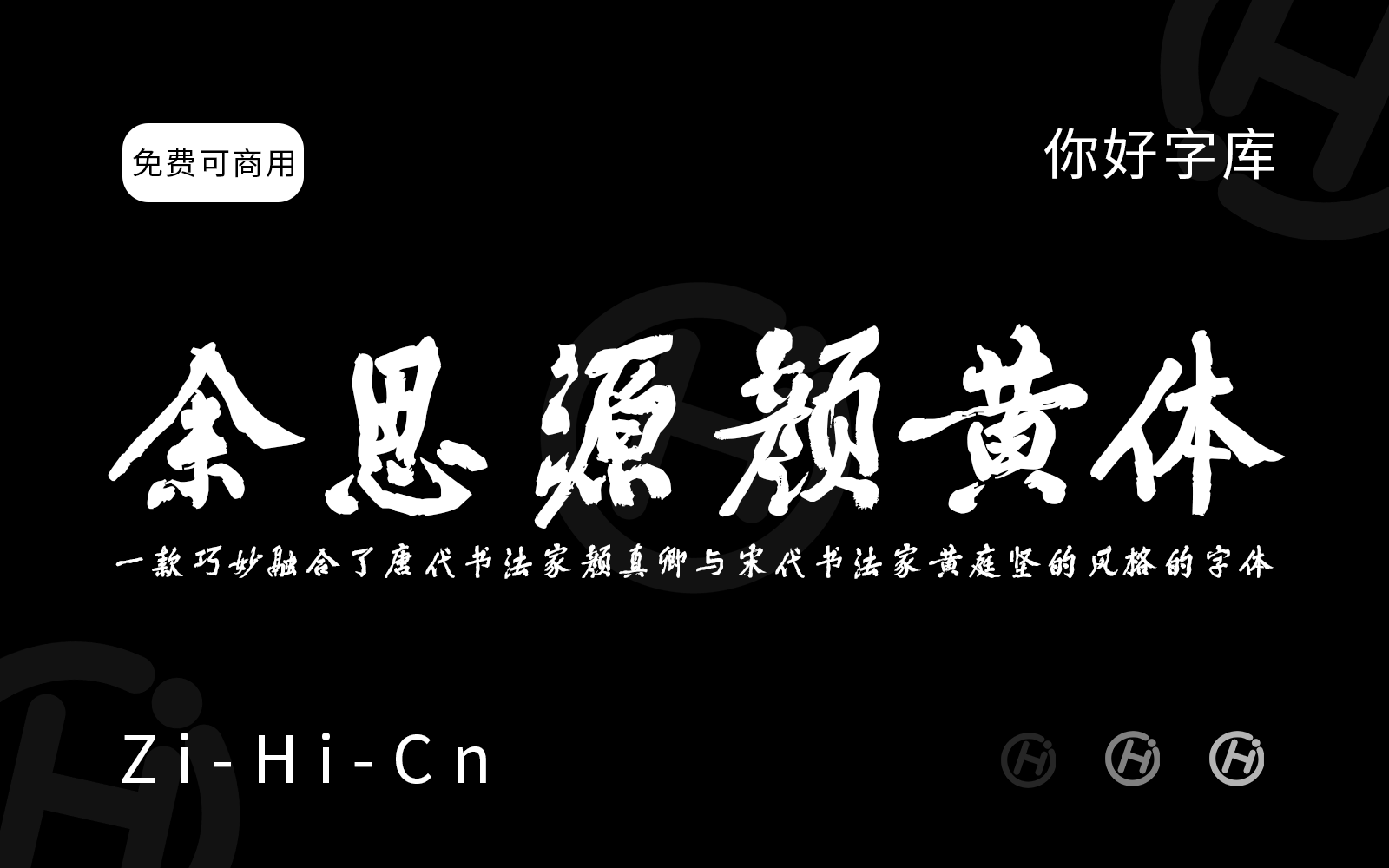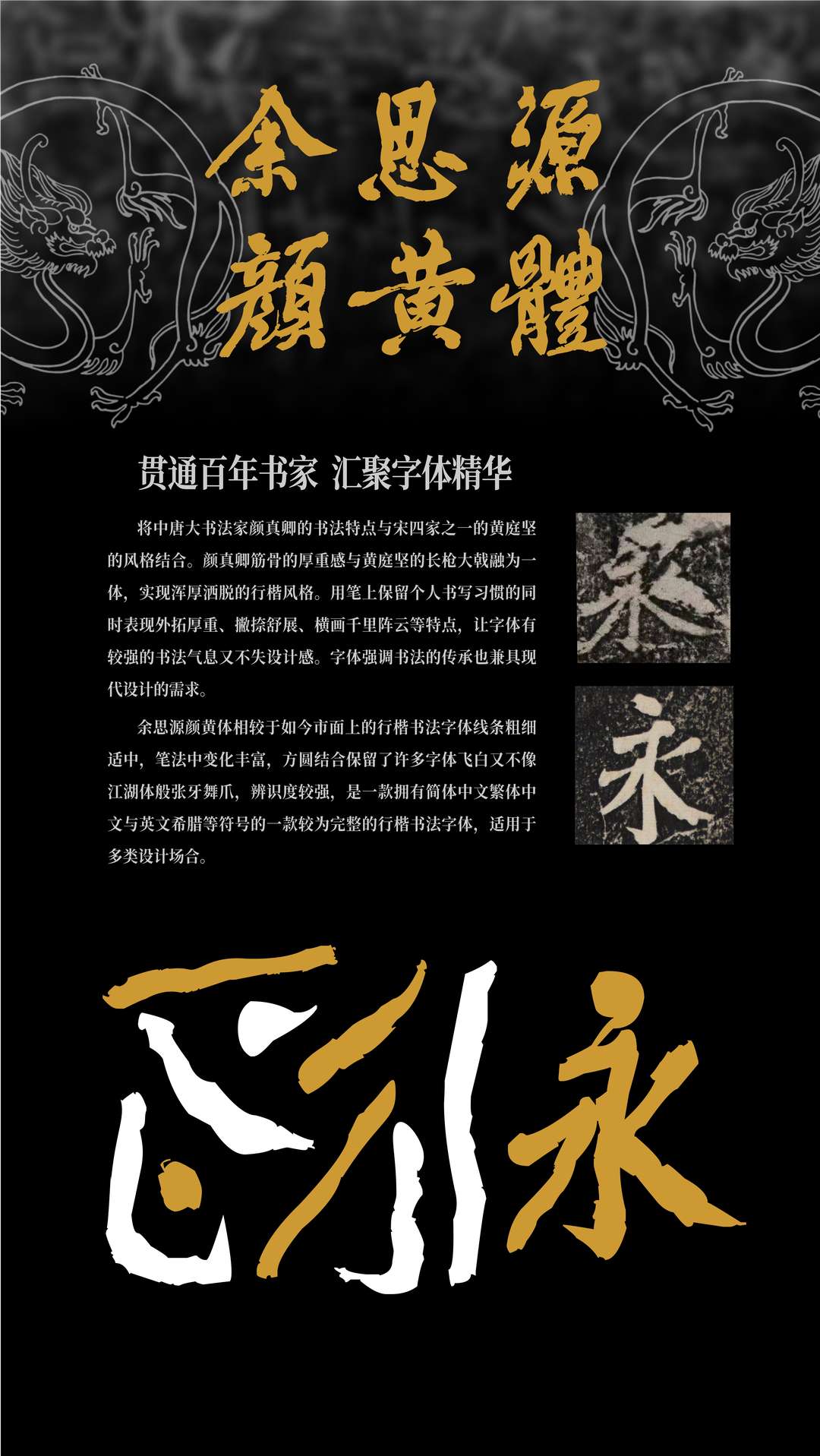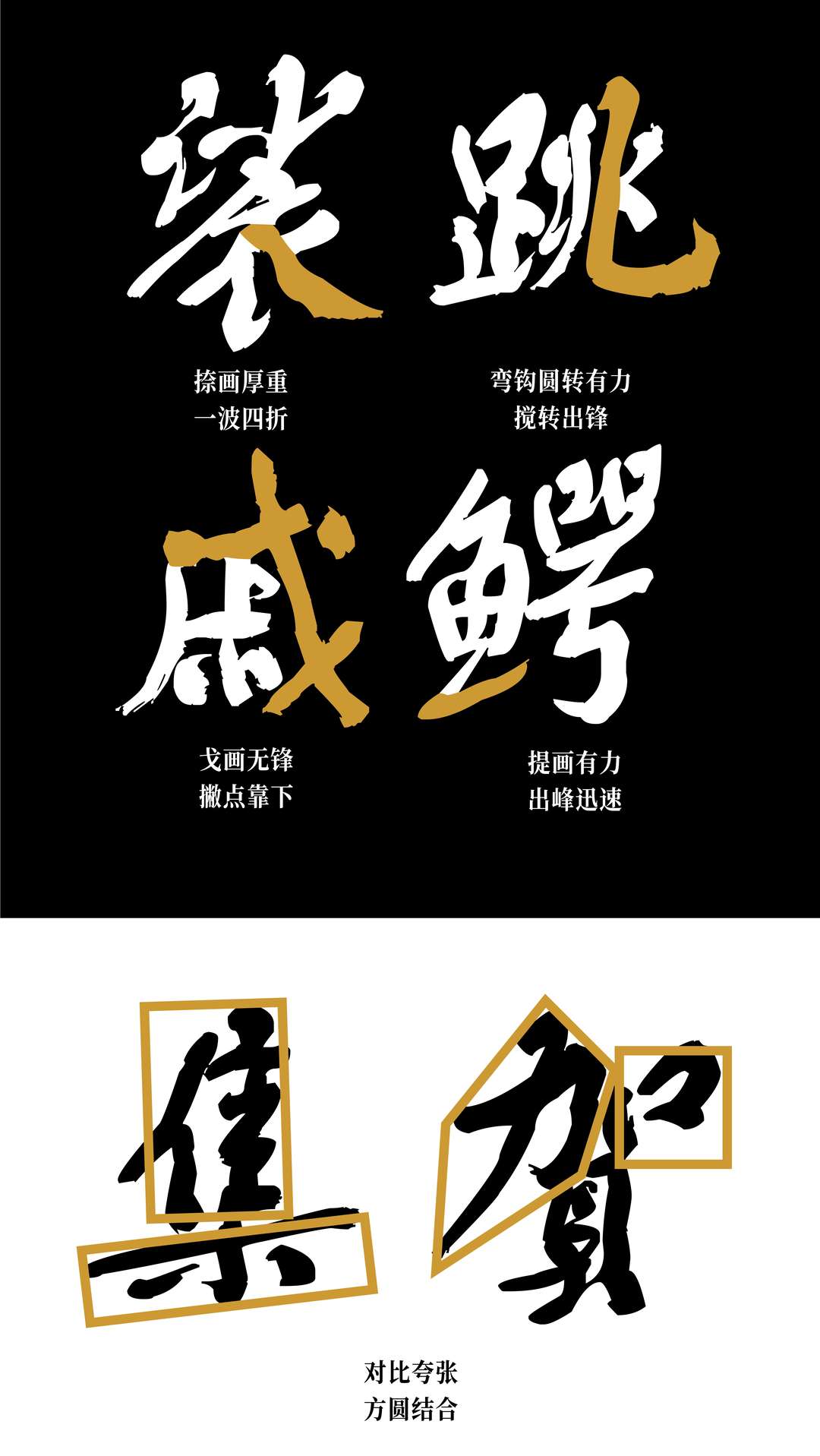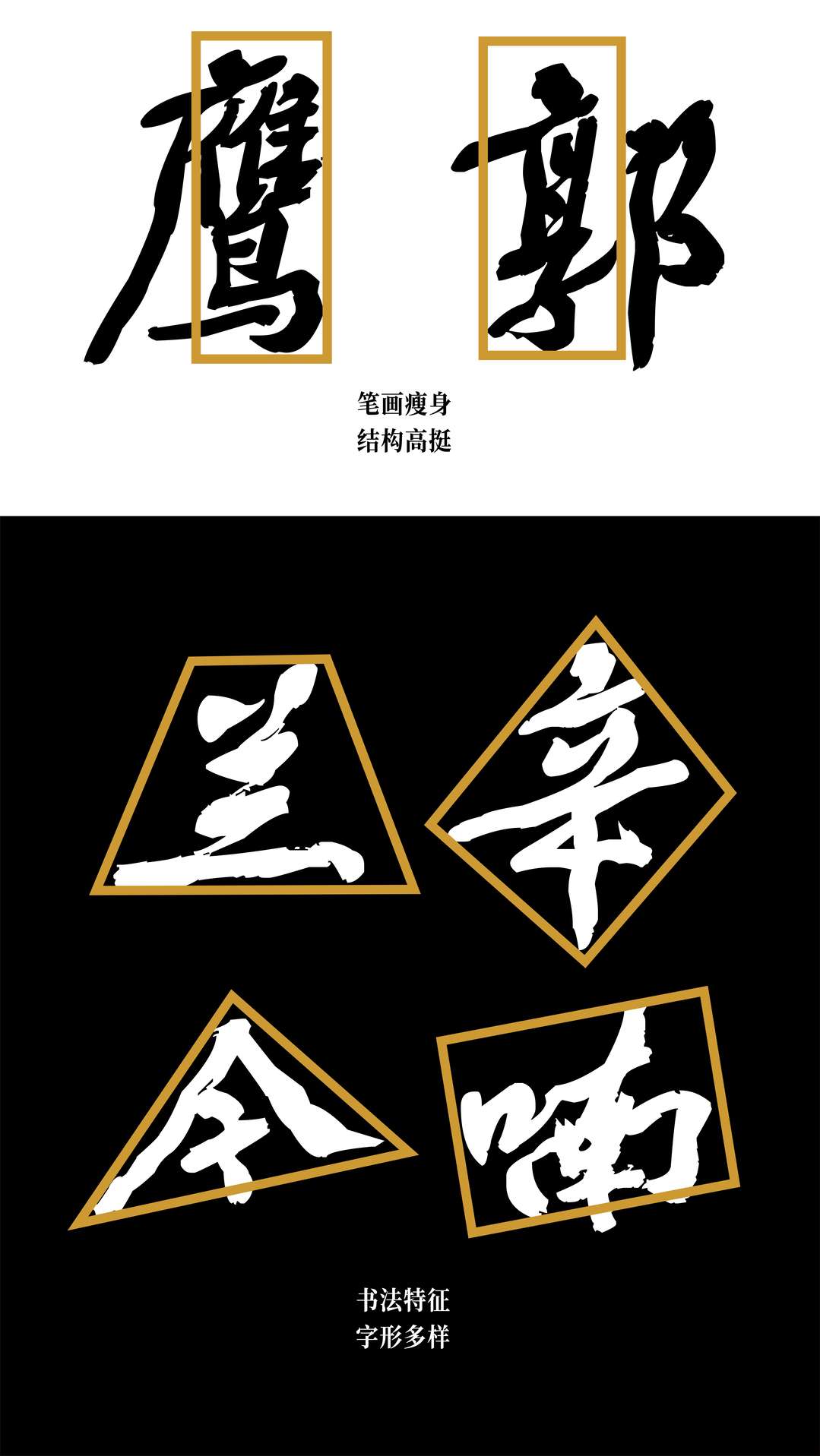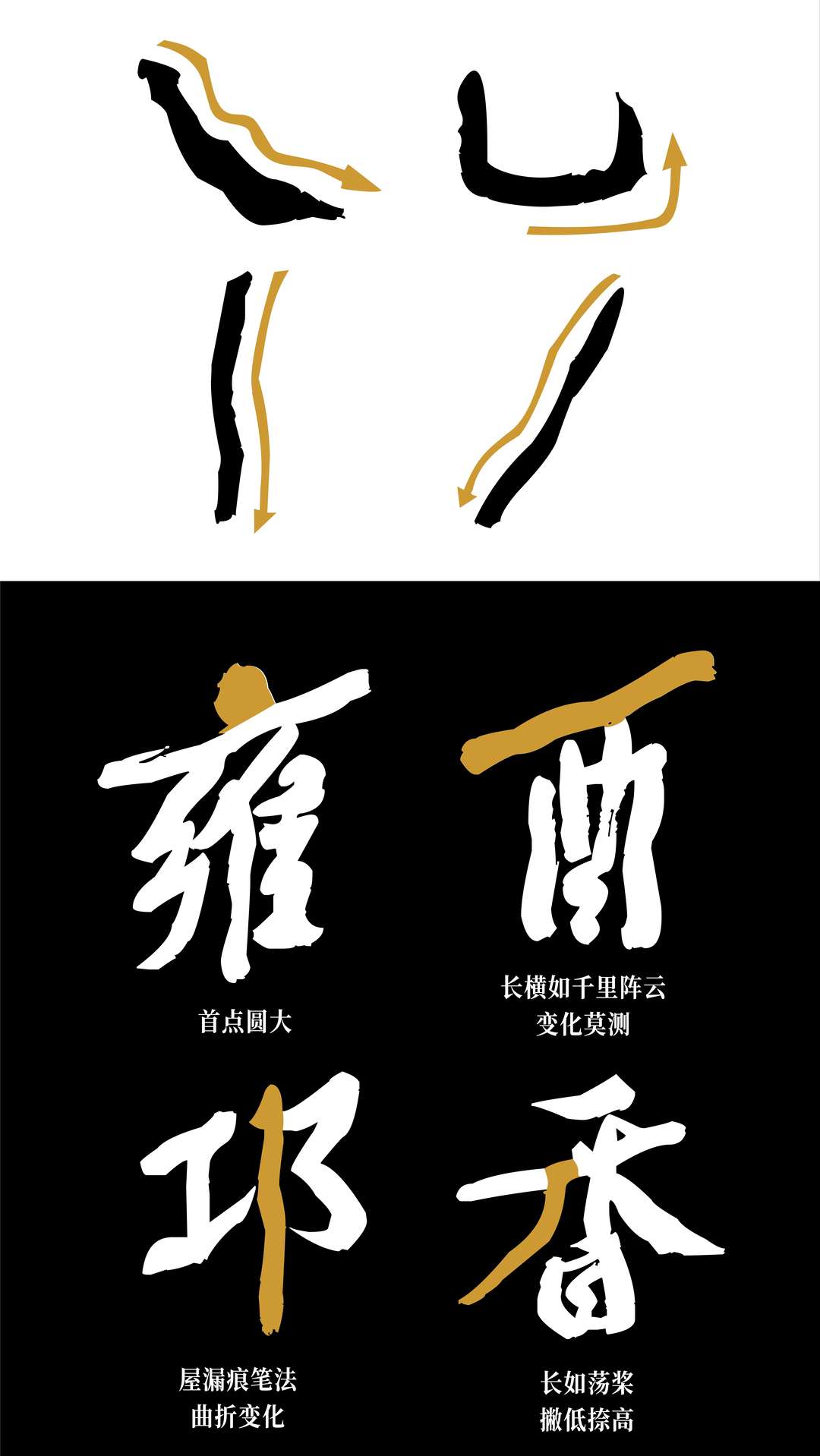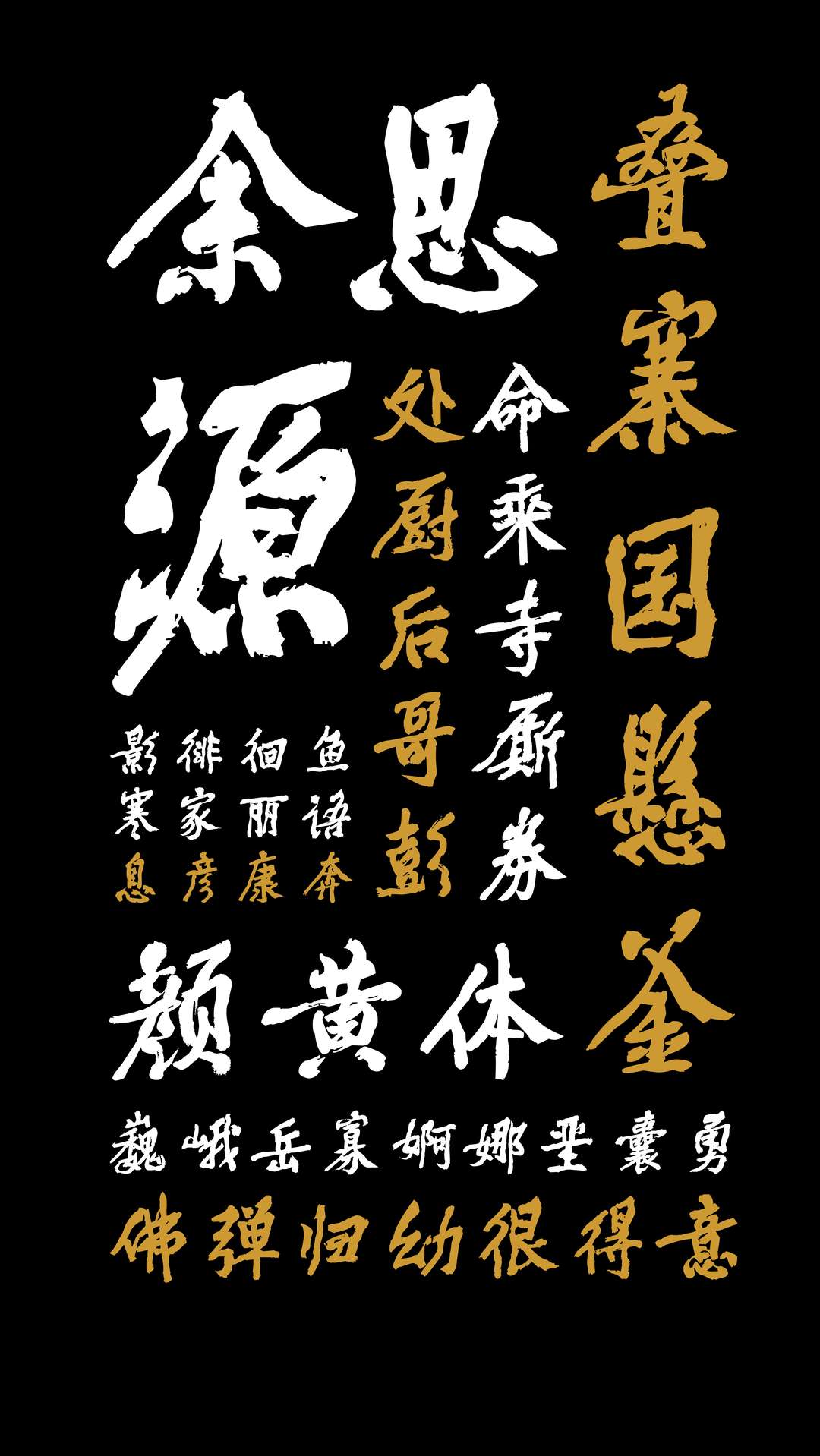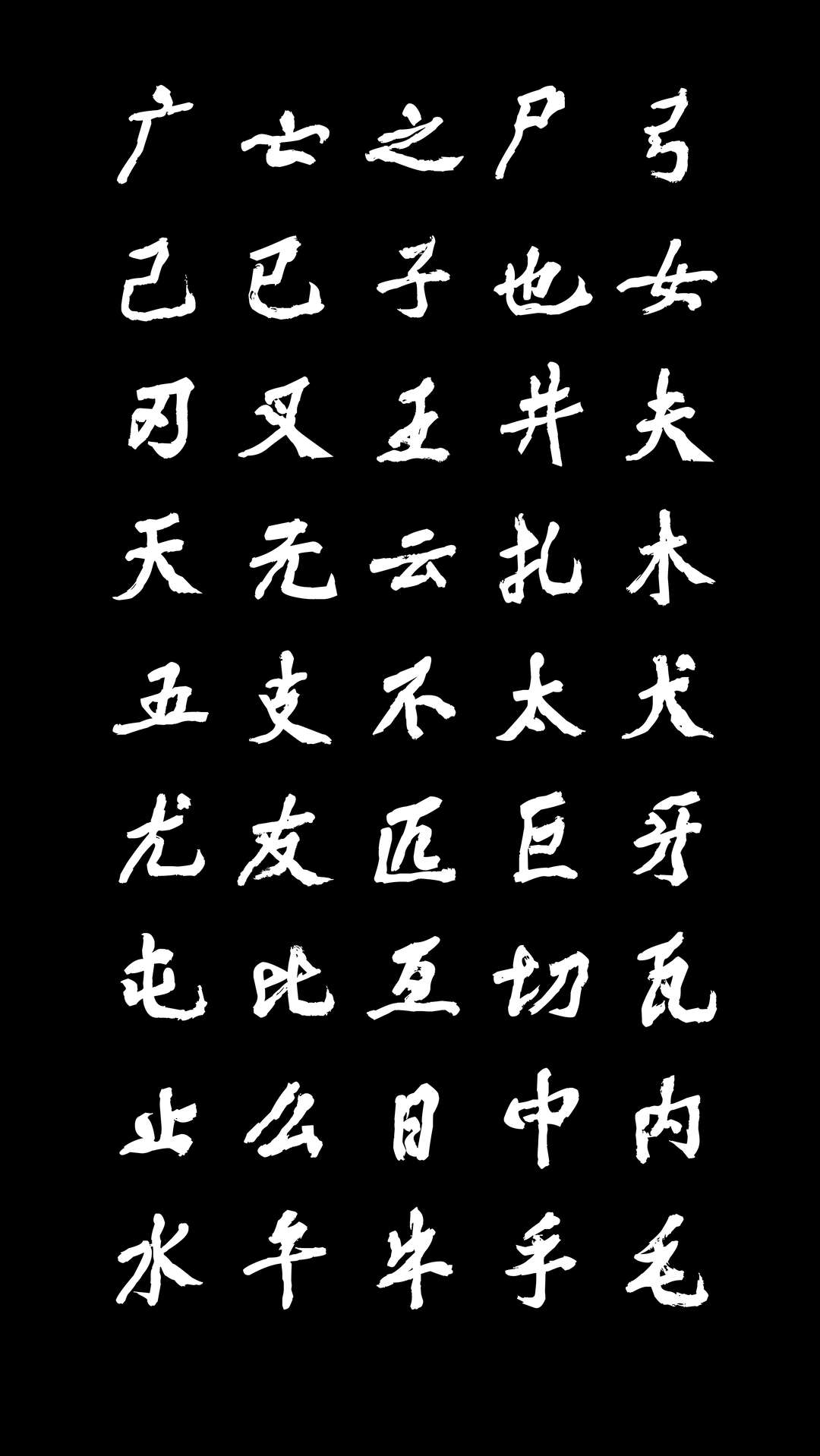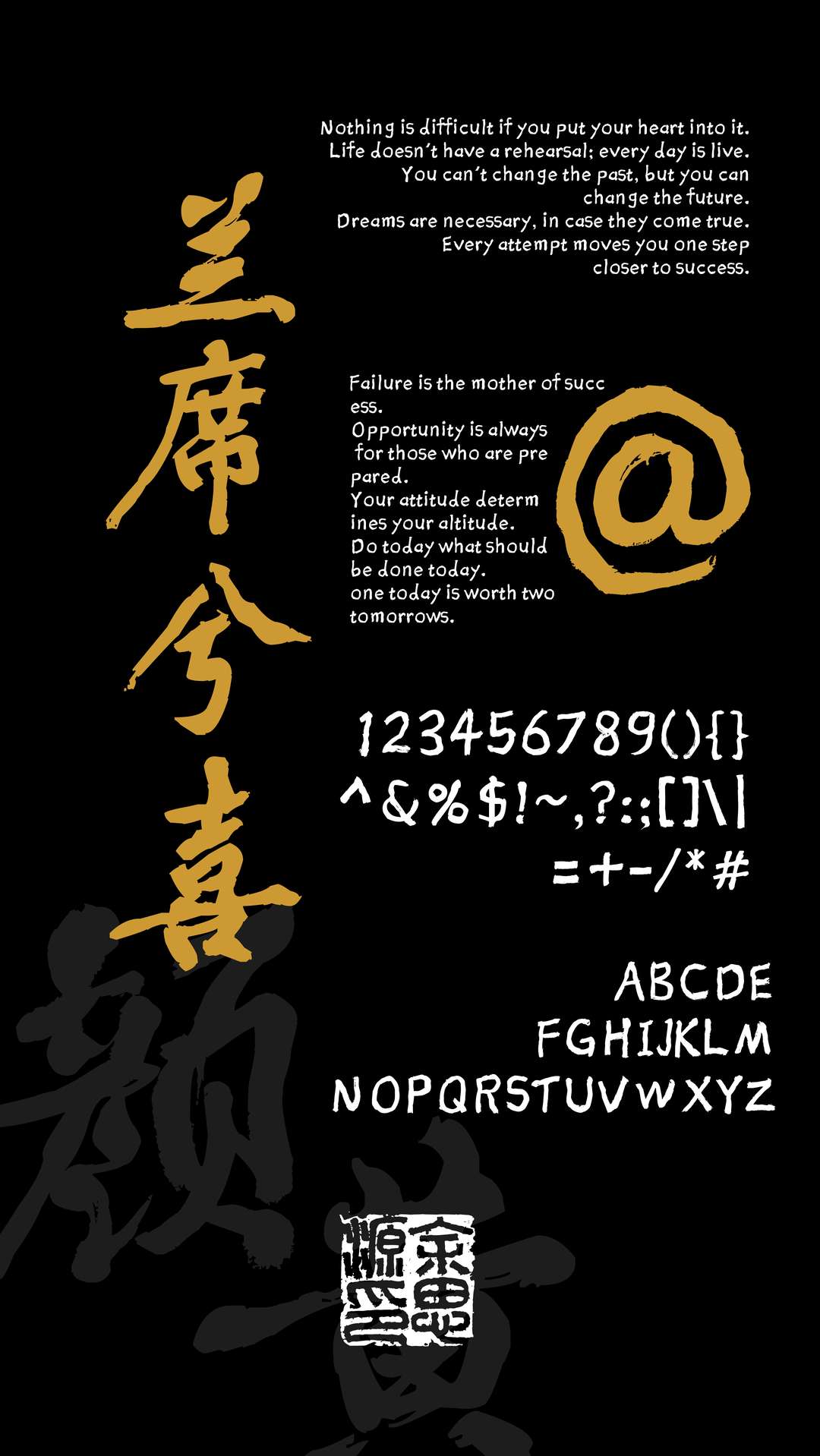
余思源颜黄体
“余思源颜黄体”是一款免费的行楷书法字体,巧妙融合了唐代书法家颜真卿与宋代书法家黄庭坚的风格,兼具传统书法韵味与现代设计实用性。它以颜真卿书法中筋骨厚重的力量感为基础,融入黄庭坚长枪大戟般的纵横气势,呈现出浑厚洒脱的行楷风貌。
在用笔上,这款字体保留了个人书写的自然习惯,笔画外拓厚重,撇捺舒展自如,横画如“千里阵云”般开阔大气,充满书法气息。相较于市面上的行楷字体,它的线条粗细适中,变化丰富,方圆结合,既有飞白的灵动,又避免了“江湖体”那种过于张扬的夸张感,辨识度高,兼顾美感与可读性。
字体包含简体中文、繁体中文、英文、希腊文及多种符号,字符集较为完整,覆盖GB2312标准(约6763个汉字)及扩展字符,总数约7000多个。